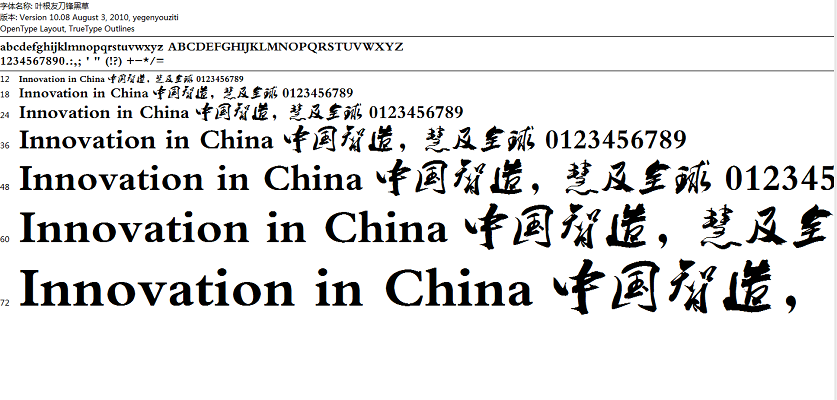
叶根友刀锋黑草
叶根友刀锋黑草是一款非常受用户欢迎的行草类字体,字体风格浑厚,如刀刻一般,同时又不失美感,是力与美的结合,感兴趣的朋友们快来下载吧!
字体介绍:
该字体是原毛笔行书基础上的又一姊妹篇书法行草类字库。
字体风格浑厚,借鉴了历代着名书法家王铎以及浙派书法家沙孟海先生和本人所欣赏的温州籍书法名家林剑丹先生的书体胫骨流派。
该字体和2007年创作的“叶根友毛笔行书简体”也有着一定的风格延续,在字的结构上比“毛笔行书简体”更加的紧凑和具有书法意象之美。
非常喜欢这个字体,很酷!很帅气,做海报经常用的。